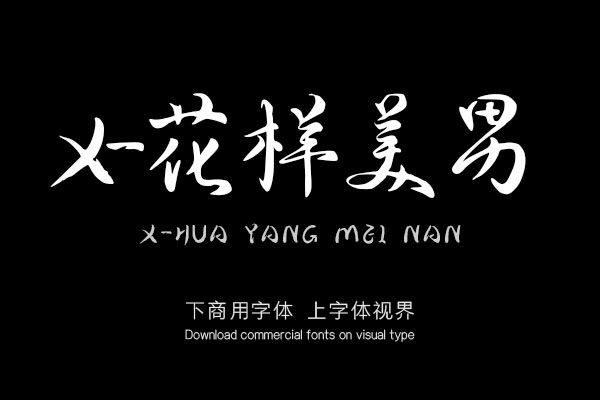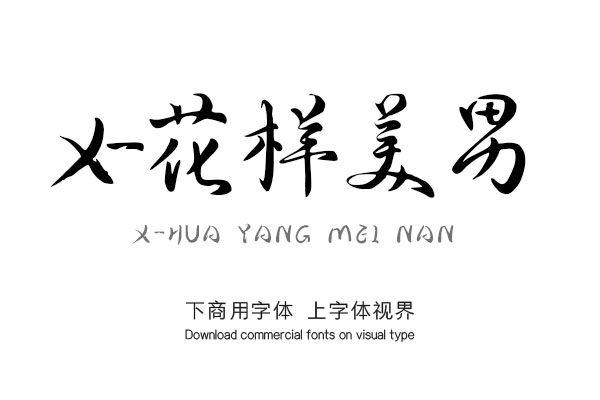
春风十里,万物复苏。你看,窗外、街边,粉白色是的杏花,粉色的是樱花,有着深紫红色叶子的是紫叶李……
每朵花都使劲浑身解数迎接春天,争先恐后地展现撩人的姿态。风一吹来,柔软轻盈的花瓣片片凋落,美不胜收。如同XFont这款“会撩”的花样美男字体。
字形偏方圆,每个笔画都流畅饱满,使用了毛笔书法中“左收”的书写理念。大量尾端的左收勾画,保留了字体尾端圆润的质感,呈现出清秀的形态。
字体笔画上轻下重,左轻右重,横画、折弯钩画的回锋收笔拉出一个饱满的勾,像行将舒展的花骨朵。
竖画的起笔微微顿笔,尾端拉出一个纤长的回笔,亦使笔画重心下移,显得稳重大方。
英文字符的设计则以圆润为主,不同于千篇一律的印刷体,笔画更具有手写感。
像春风吹拂的花朵,亦像沉稳镇定的少年。
应用:
糅合了书法特质的字体,适宜的场景更丰富了。
广告招牌、游戏场景、古风绘画、出版印刷,都能很好地融合。